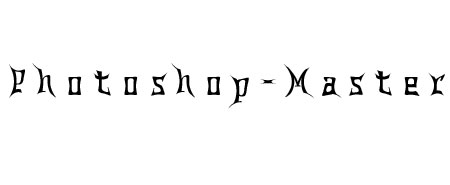
Дополнения Шрифты Татьяна Гапонова 26 июля 2009 Шрифт - China Town Красивый шрифт без поддержки русского языка/ Скачать Шрифт - China Town
Великолепный Шрифт
Хороший шрифт, жаль что без русского языка.
Замечательный шрифт! Может пригодиться для создания разных эмблем и работ ФШ)